免费手写体字体下载合集,个人签名和品牌标语轻松制作
做品牌标语或者个人签名的时候,黑体和宋体总显得太正式、太冷冰冰的。手写字体能让人感觉到温度,像是有人亲手写上去的,客户看了也会觉得更有亲和力。我自己做文创项目的时候,经常需要这种带人情味的文字效果。找免费手写体字体下载渠道攒了一段时间,这篇文章把几个实用的平台整理出来,从真实手写模拟到可安装的字体文件都有,覆盖中文和英文资源。
字由在中文手写体方面的覆盖做得很好,平台收录的手写体超过一千款,其中不少标注了免费商用。像鸿雷板书简体这种,笔画带有自然的不规则感,做品牌标语或者文创包装很显温度。杨任东竹石体结构舒展,偏文化气质,做展览标题或者书籍封面很合适。站酷庆科黄油体俏皮可爱,做烘焙品牌或者儿童相关的设计特别贴切。这些免费手写体字体下载资源都通过了授权审核,商用时比较放心。
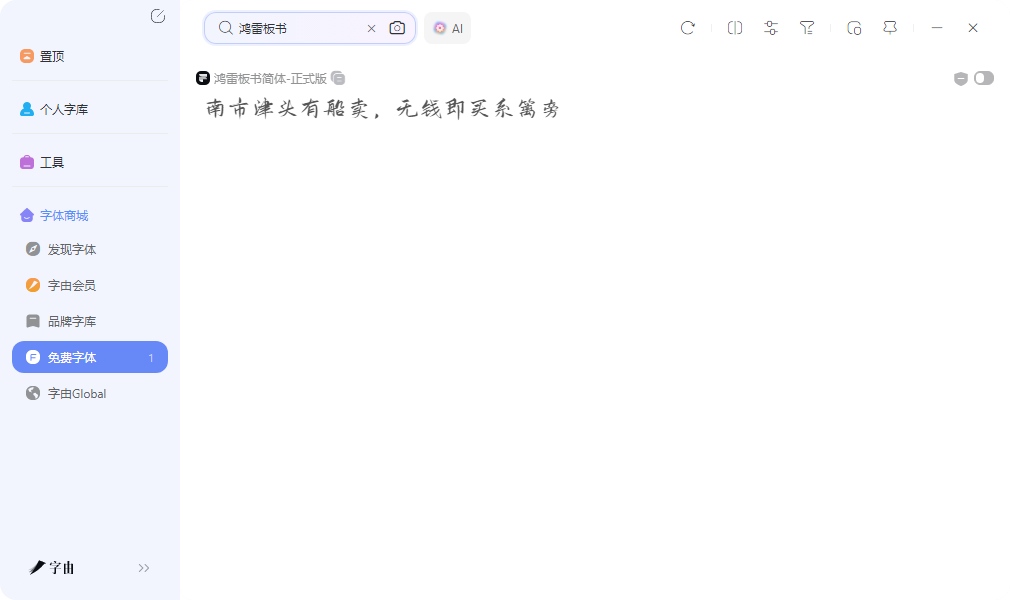
找手写体的时候,字由的 AI 配字功能可以省不少时间。输入"手写、文艺、品牌、温度"这类关键词,系统会推荐几款风格匹配的手写体组合,每款都附带预览效果。推荐结果里有不少标注免费商用的选项,看到合适的可以直接激活,在 PS、AI 等设计软件里立刻调用。收藏分组功能也实用,把常用的手写体归到一个组,做新项目时直接打开调用,不用重新翻找。
AI 字效功能则适合做手写风格的特效标题。模板库里有不少模拟毛笔质感、水彩晕染、马克笔效果的样式,选中后输入文案就能生成带特效的手写风格图片。生成的 PNG 背景透明,可以直接放进海报或者电商详情页里。AI 识字功能也值得一提,看到一张手写风格的海报想知道用的是什么字体,上传图片几秒就能识别出来。
2、10015 Tools
10015 Tools 提供了一个 Text to Handwriting Converter,是一个在线文字转手写工具。操作流程很直接,在文本区域输入内容,然后从下拉菜单中选择字体样式,目前支持 Gloria Hallelujah 等手写风格字体。接着可以调整字号、墨水颜色、纸张类型等参数,设置好后系统会生成模拟手写效果的输出页面。
这个工具支持多页输出,对于需要生成长段手写文字的场合比较实用。你可以选白色纸张或者其他纸张背景,墨水颜色也能调,模拟不同笔的效果。生成的结果可以打印出来,或者保存为 PDF 文件。对于需要快速获得手写风格文字、但又不想安装字体的用户来说,这种在线转换的方式很轻便。不过它的字体选择相对有限,主要是英文字体,中文支持可能不够全面。
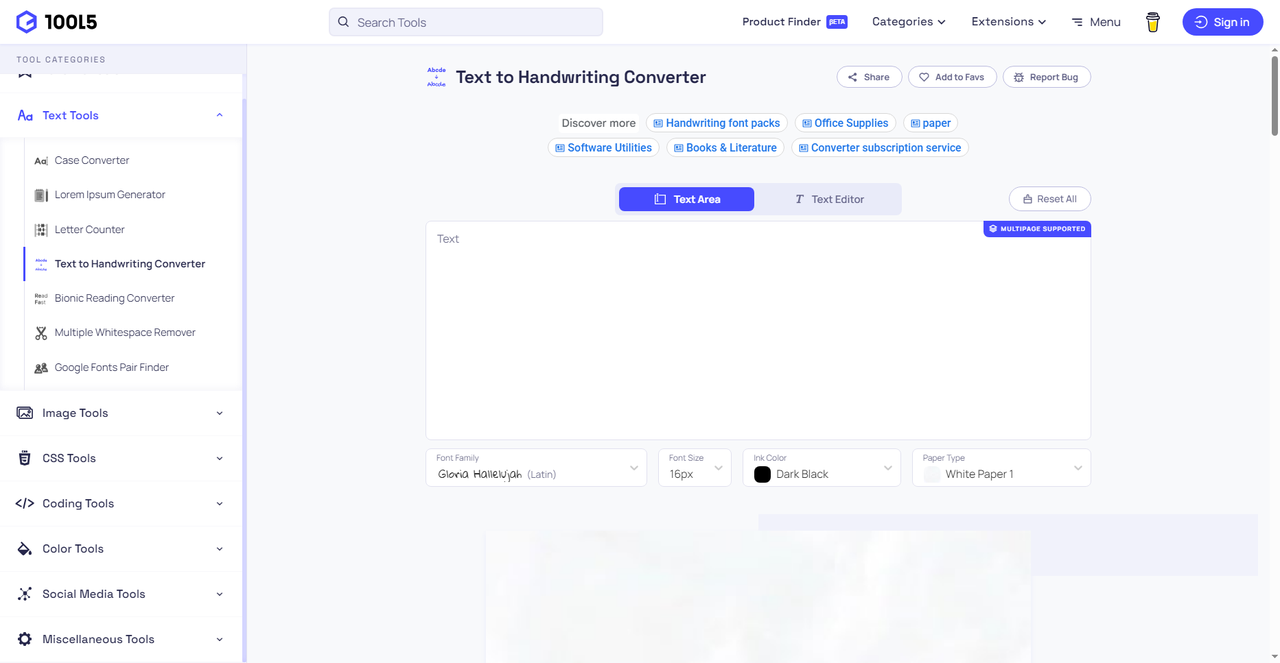
3、Handtextai
Handtextai 是一个专注文字转手写的工具,效果做得相当真实。平台支持 Print 和 Photo 两种输出模式,Print 模式生成适合打印的手写页面,Photo 模式则模拟真实拍照的手写纸张效果。你可以调整纸张类型、排版格式、页面方向等参数,还能导入 PDF 或 DOCX 文件直接转换。
它的手写效果确实挺自然的,不像有些工具转换出来一看就很假。对于需要批量生成手写笔记、手账内容、或者模拟真实信件的场景,这个工具能省下大量时间。平台还支持 AI Writer 功能,可以辅助生成内容后再转手写,一条龙操作。
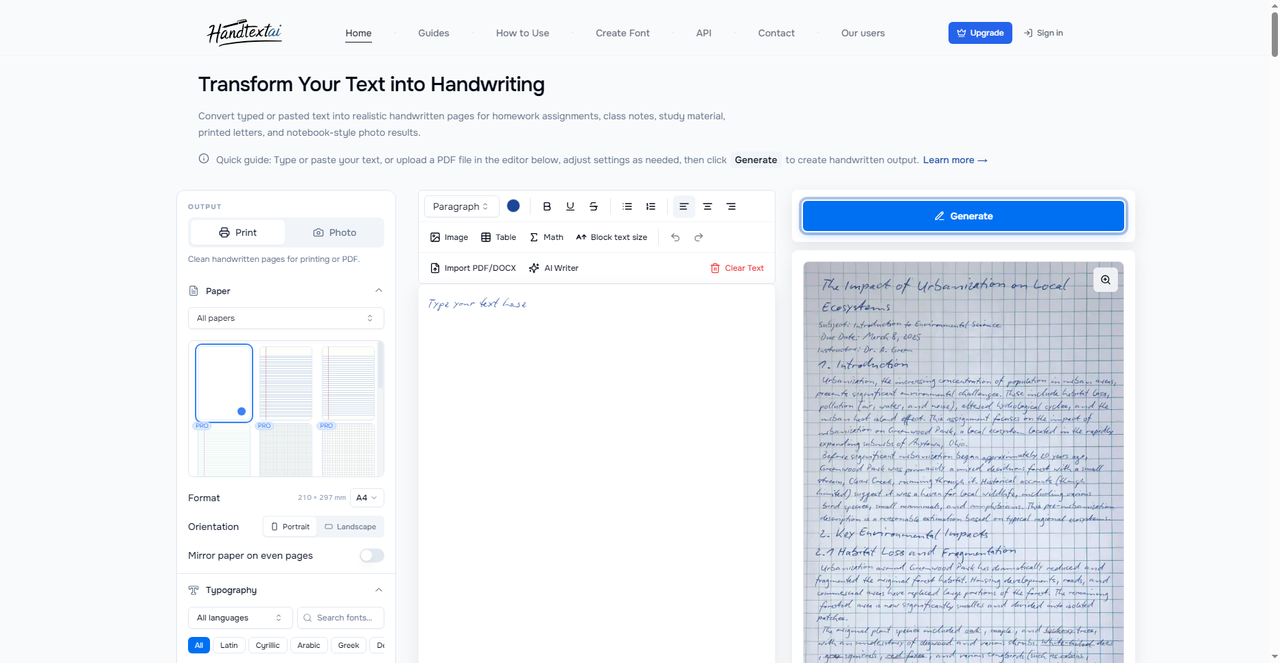
4、FontSpace Handwritten
FontSpace 的 Handwritten 分类是我收藏了很久的一个渠道,专门收录免费手写体。页面上的说明写得挺到位,手写体能给设计带来人性化的感觉,适合社交媒体配图、品牌标语、包装、邀请函等场景。平台收录的手写体风格很多,从 casual marker-style 到 smooth signature scripts 都有覆盖。
每款字体都标注了授权信息,部分支持免费商用,下载前可以确认。字体质量普遍不错,像 LiebeHeide Color Font 这种带彩色效果的、Slight Calligraphy Font 这种偏优雅书法的、Symphony Script 这种简洁手写体的,都能找到。预览图清晰,点击就能进入详情页下载。
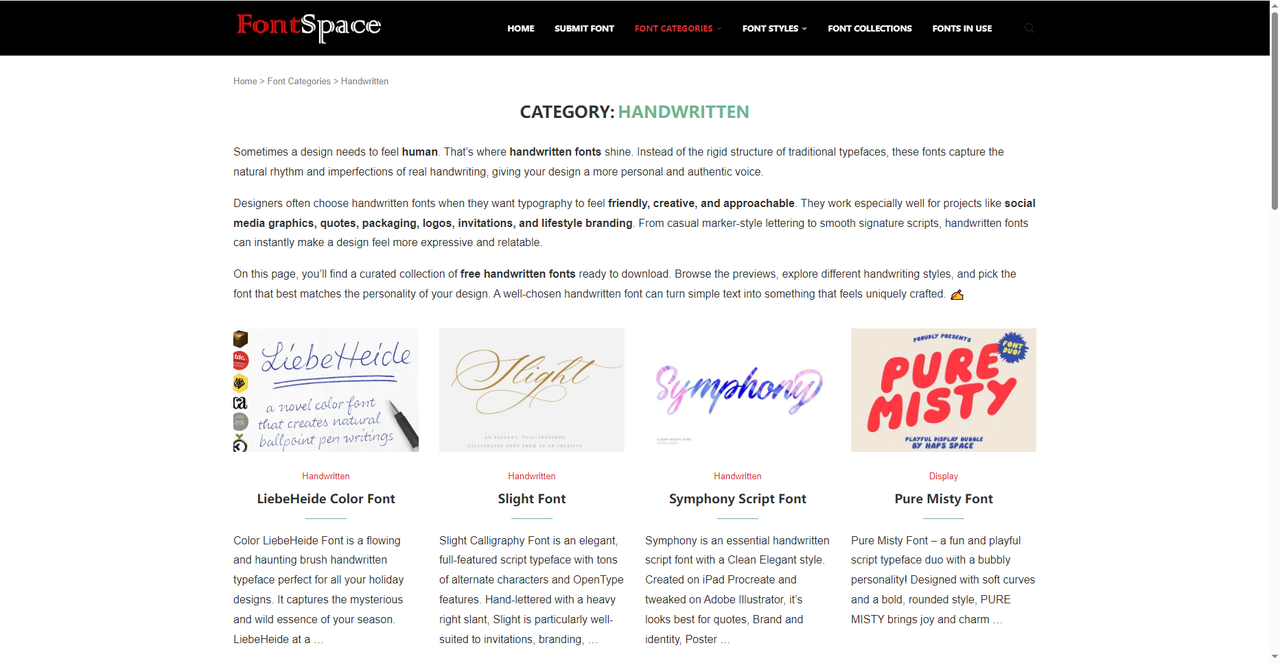
5、BFONT Handwritten
BFONT 的 Handwritten 分类也收录了不少手写体资源。首页导航有 Sans Serif、Serif、Display、Popular、Script、Calligraphy、Handwritten、Fancy、Techno 等标签,点击 Handwritten 就能快速定位。页面展示了 Stormy Youth Regular、Sunrise International Script 等字体,风格从潦草青年感到优雅连笔都有。
右侧的分类栏可以看到手写体相关的 Brush、Calligraphy、Script 等分类的资源数量,方便判断哪个分类更丰富。字体文件下载后安装到系统,在 Photoshop、Illustrator 等设计软件里就能调用。对于喜欢在多个平台对比手写体风格、找到最契合项目气质那款的人来说,BFONT 的分类浏览比较直观。这里的资源也适合和 FontSpace 互相补充,两边都逛一圈,基本能找到大部分免费手写体字体下载需求的手写体。
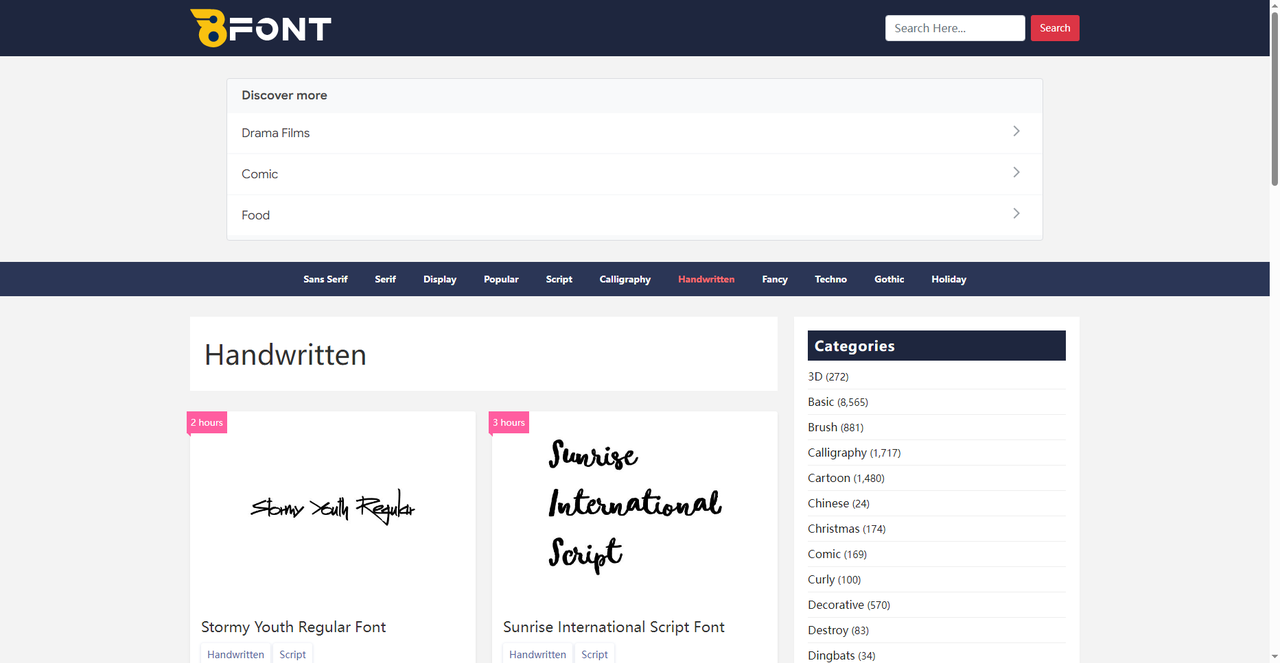
急着出一张带手写感的海报或者品牌标语,字由的中文手写体资源全、AI 字效出图快,配合免费手写体字体下载后的激活和筛选,从找字体到出成品比较顺畅。10015 Tools 和 Handtextai 适合需要模拟真实手写纸张效果、而不是安装字体的场景,Handtextai 的逼真度更高一些。FontSpace 和 BFONT 则是安装文件类手写体的主要入口,一个授权标注清晰、一个分类直观,建议都收藏着,找英文免费手写体字体下载资源的时候两边对照着看。